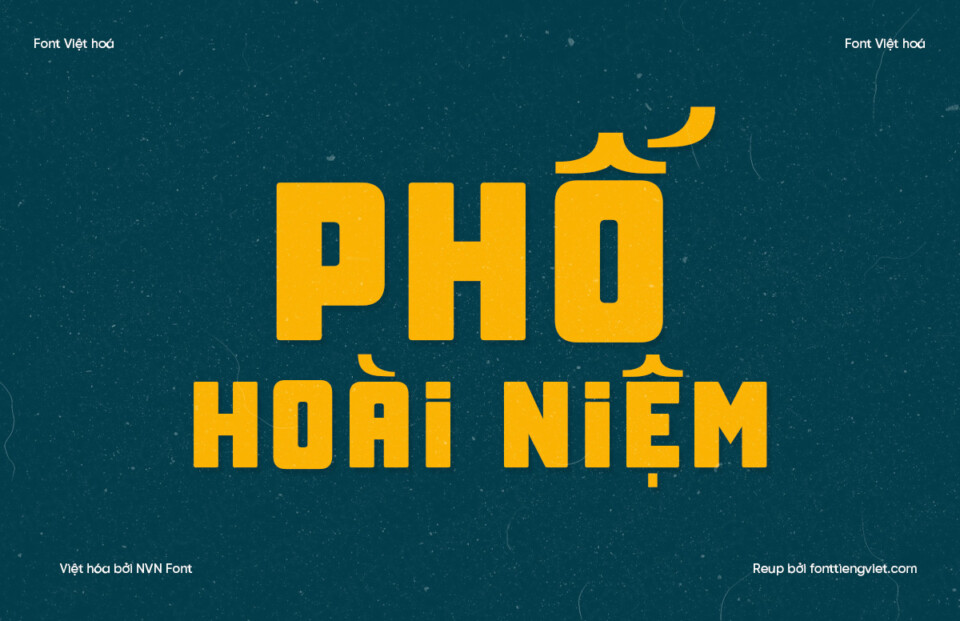
Font Việt hóa NVN Manufaktur
Giới thiệu về bộ Font Việt hóa NVN Manufaktur
Trong thế giới đồ họa hiện đại, việc lựa chọn một bộ Font Miễn Phí chất lượng luôn là ưu tiên hàng đầu của các nhà thiết kế. Font Việt hóa NVN Manufaktur nổi lên như một giải pháp hoàn hảo cho những ai yêu thích phong cách tối giản nhưng vẫn đầy cá tính. Đây là một bộ font chữ được tinh chỉnh kỹ lưỡng về dấu tiếng Việt, giúp người dùng dễ dàng ứng dụng vào các dự án truyền thông, trình chiếu học tập hay thiết kế thương hiệu mà không lo lỗi hiển thị. Với đường nét chắc chắn và hình khối rõ ràng, bộ font này mang lại cảm giác chuyên nghiệp và hiện đại cho mọi tác phẩm nghệ thuật.
Nguồn gốc và đặc điểm thiết kế của NVN Manufaktur
Bộ Font Việt hóa NVN Manufaktur được lấy cảm hứng từ các bảng hiệu kỹ thuật và công nghiệp cũ, tạo nên một vẻ ngoài vừa cổ điển vừa tân tiến. Điểm mạnh của nó nằm ở cấu trúc hình học cân đối, các nét chữ có độ dày vừa phải giúp tăng cường khả năng đọc trên cả màn hình kỹ thuật số lẫn bản in. Đối với các bạn học sinh và giáo viên, việc sử dụng font chữ này trong các bài thuyết trình giảng dạy sẽ giúp nội dung trở nên thu hút và dễ tiếp cận hơn đối với người xem.
Lý do nên sử dụng Font Việt hóa NVN Manufaktur trong thiết kế
Sở dĩ Font Việt hóa NVN Manufaktur được cộng đồng thiết kế tại Việt Nam ưa chuộng là bởi tính linh hoạt cao. Bạn có thể sử dụng nó cho nhiều mục đích khác nhau từ làm tiêu đề báo chí, thiết kế banner quảng cáo đến tạo mẫu layout cho website. Việc đã được Việt hóa hoàn chỉnh giúp các ký tự có dấu như “ă, â, đ, ơ, ư” trông hài hòa tuyệt đối với các ký tự Latinh, loại bỏ hoàn toàn tình trạng lệch dòng hay sai khoảng cách thường gặp ở các font ngoại nhập chưa qua chỉnh sửa.
Ứng dụng thực tế trong môi trường giáo dục và đồ họa
Trong môi trường nhà trường, Font Việt hóa NVN Manufaktur là công cụ đắc lực để thiết kế các tờ rơi thông báo, bằng khen hoặc trang trí báo tường. Sự rõ ràng của bộ font giúp các em học sinh dễ dàng nắm bắt thông tin quan trọng. Đối với các nhà thiết kế chuyên nghiệp, đây là lựa chọn tuyệt vời để tạo ra các bộ nhận diện thương hiệu mang hơi hướng kỹ thuật, kiến trúc hoặc thủ công mỹ nghệ. Khả năng kết hợp của nó với các font chữ không chân khác cũng rất đa dạng, tạo nên sự phong phú cho kho tài nguyên thiết kế của bạn.
Kết luận về giá trị của bộ font